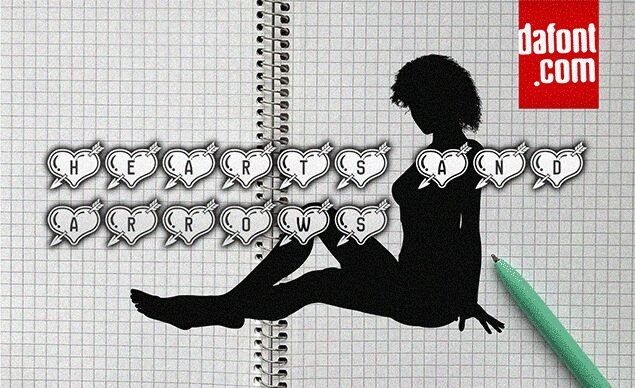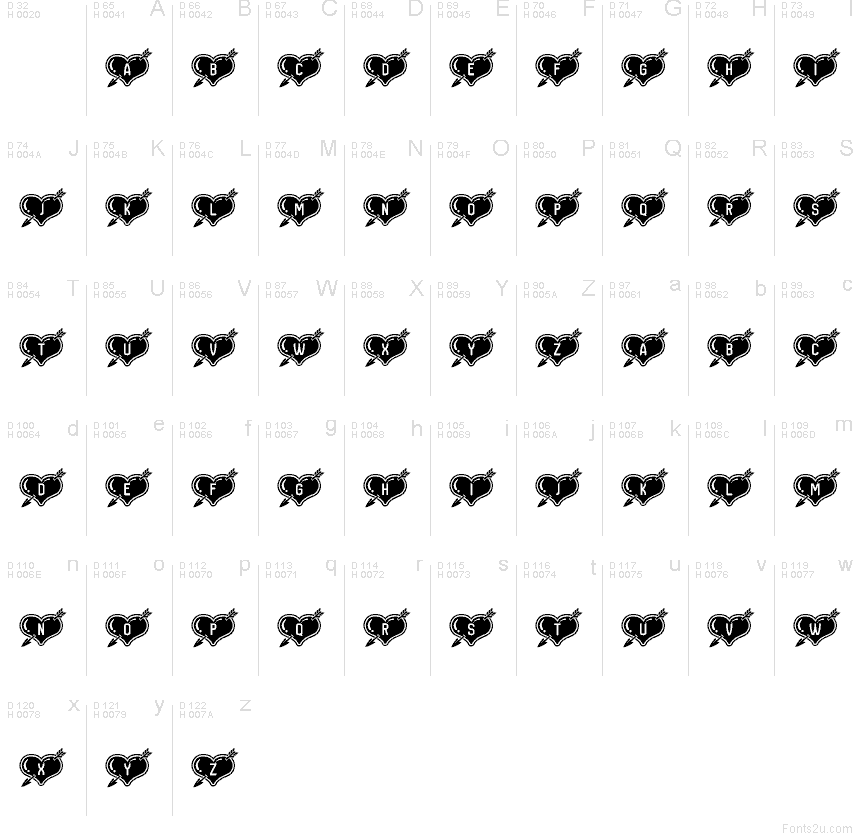
Hearts and Arrows Retro Regular
Hearts and Arrows Retro od Vladimira Nikolicě je bezplatné valentýnské písmo, které promění každý znak v emblém srdce se šípem. Opakující se silueta prostřeleného srdce, výrazná černá výplň a světlé vnitřní linky dodávají písmu vzhled nálepek, který evokuje klasickou romantiku přáníček spíše než běžný dekorativní styl.
Pro valentýnky, pozvánky na party, dárkové visačky, obaly na sladkosti či nadpisy v památnících funguje Hearts and Arrows Retro nejlépe jako doplněk krátkých slov nebo jako výrazný titulek. Protože každé písmeno tvoří samostatný srdcový odznak, hodí se také pro rámování popisků fotek, příspěvků na sociálních sítích a tematických štítků, kde má samotný motiv doplňovat sdělení.